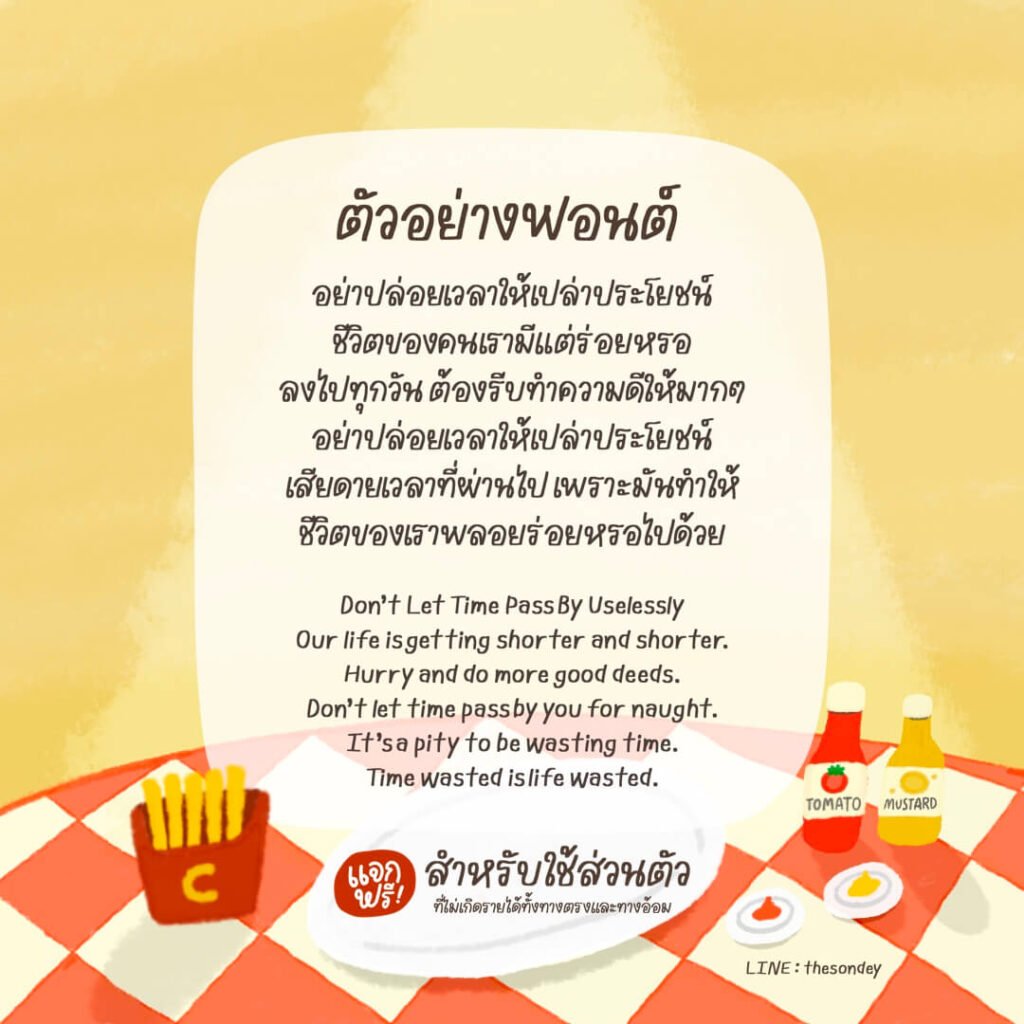
เฟรนช์ฟรายส์ (PG Frenchfries)
ฟอนต์ลายมือสไตล์น่ารักปุ๊กปิ๊ก อ่านง่าย รองรับ Microsoft, Photoshop, Illustrator, CapCut, ibisPaint, Procreate, Good Note และแอปฯ ต่างๆ ที่มีให้ติดตั้งฟอนต์